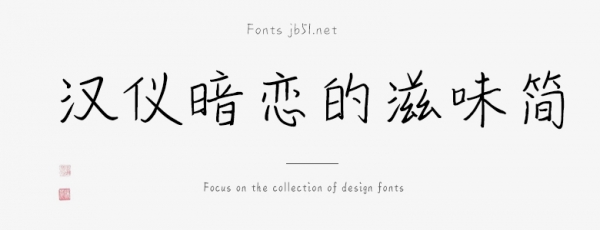
漢儀暗戀的滋味簡(jiǎn)是由漢儀字庫(kù)出品,字體筆觸纖細(xì),字形端正,具有很好的視覺(jué)感,適合應(yīng)用于藝術(shù)設(shè)計(jì)、平面宣傳設(shè)計(jì)、網(wǎng)頁(yè)設(shè)計(jì),書(shū)法字帖等領(lǐng)域,需要的朋友可以前來(lái)本站下載。